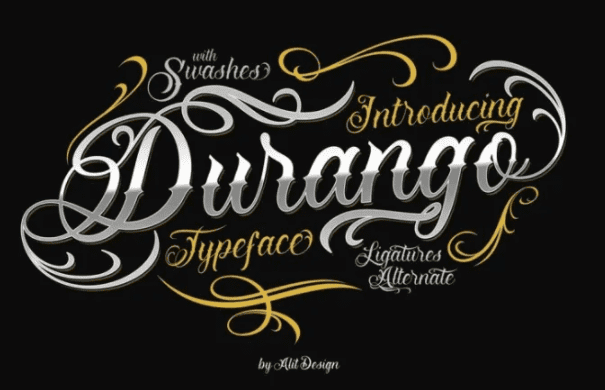
Название: Durango Font (2021)
Представляем вашему вниманию шрифт Durango!
Шрифт Durango вдохновлен стилем шрифта татуировок в мексиканском регионе. Смелый, крутой и синонимичный стилю банд или гангстеров в Латинской Америке. В дополнение к шрифту Durango вы также получаете пакет Swash, который очень подходит для сочетания со шрифтом Durango, пример использования Swash со шрифтом Durango можно увидеть на плакате предварительного просмотра шрифта Durango.
Его можно использовать для оформления упаковки алкогольных напитков, дизайна помад, парикмахерских и так далее с концепцией викторианской классики.
Название: Durango Font (2021)
Представляем вашему вниманию шрифт Durango!
Шрифт Durango вдохновлен стилем шрифта татуировок в мексиканском регионе. Смелый, крутой и синонимичный стилю банд или гангстеров в Латинской Америке. В дополнение к шрифту Durango вы также получаете пакет Swash, который очень подходит для сочетания со шрифтом Durango, пример использования Swash со шрифтом Durango можно увидеть на плакате предварительного просмотра шрифта Durango.
Его можно использовать для оформления упаковки алкогольных напитков, дизайна помад, парикмахерских и так далее с концепцией викторианской классики.